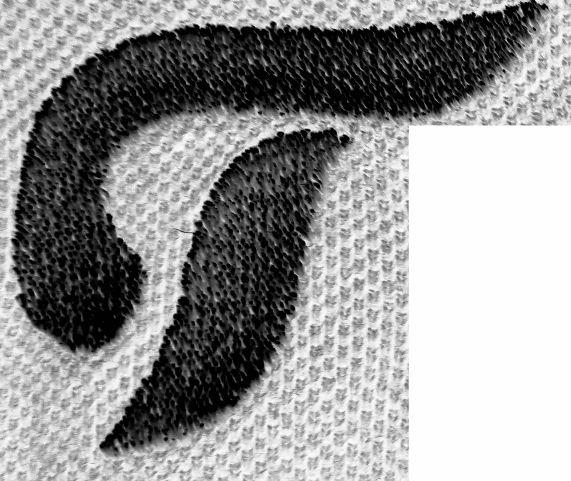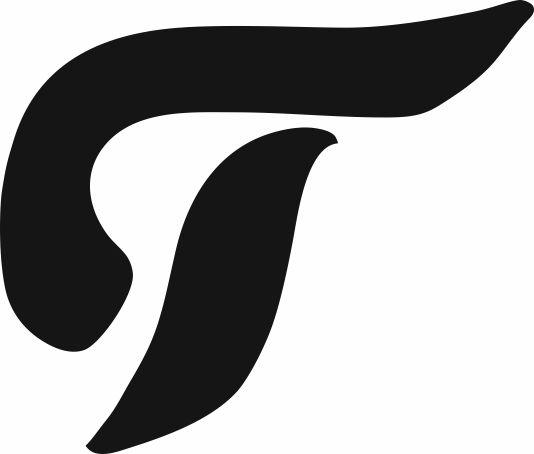
Schriftart vom Stick gesucht!
ich suche die Schriftart von diesem gestickten T:
Nachgebaut sieht es so aus:
Leider gibt mir Whatthefont nichts richtiges an...
Gibt es wirklich nur diesen einen Buchstaben? Dann ist die Wahrscheinlichkeit, das der handgemacht ist und nicht aus einer Schrift kommt recht groß. Und wird der nur auf dem Shirt gestickt eingesetzt oder gibt es die Marke noch anders wo?